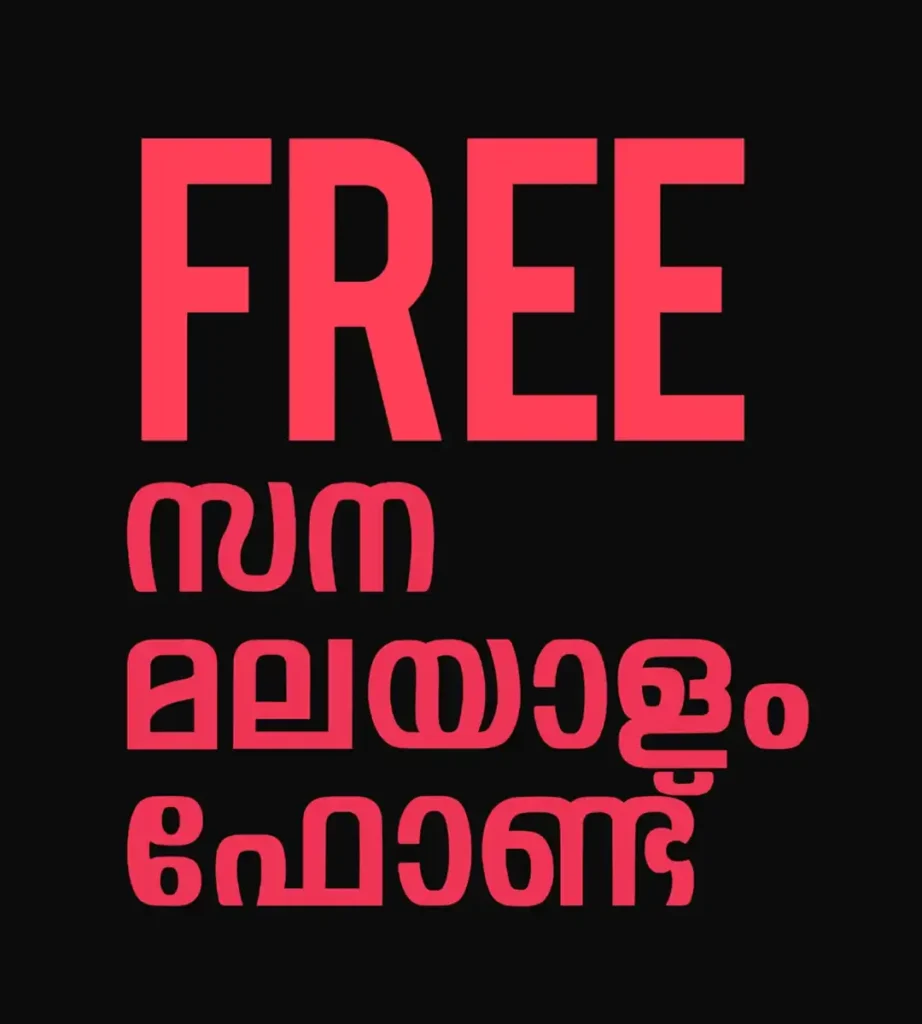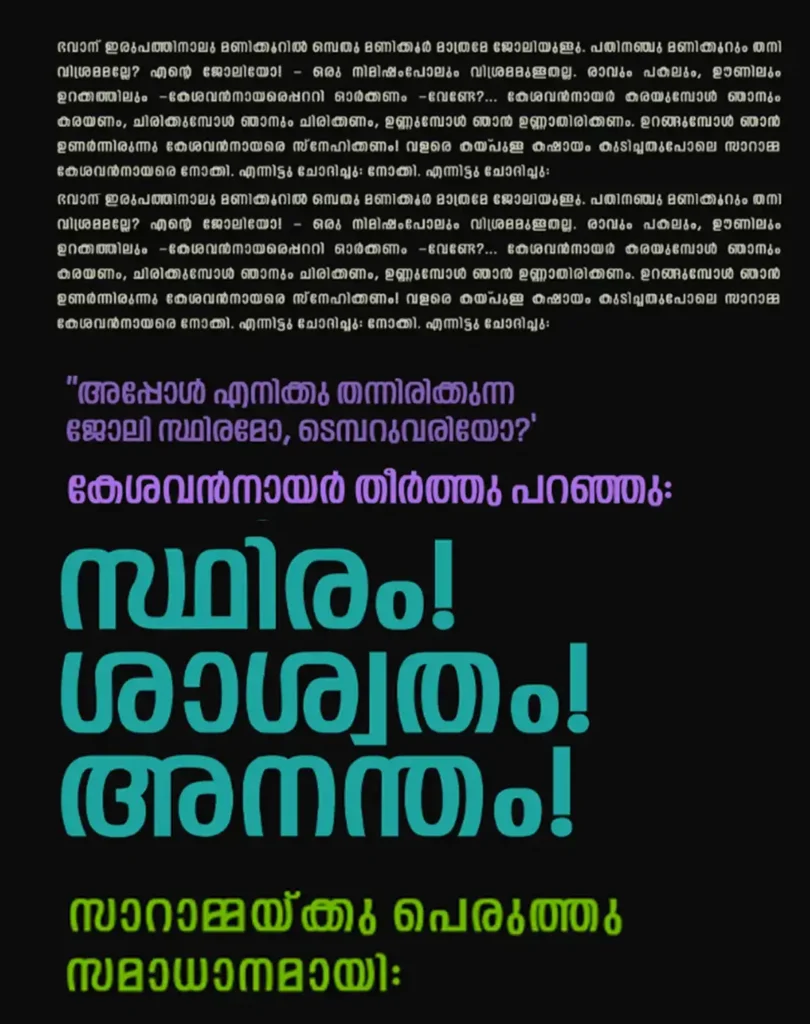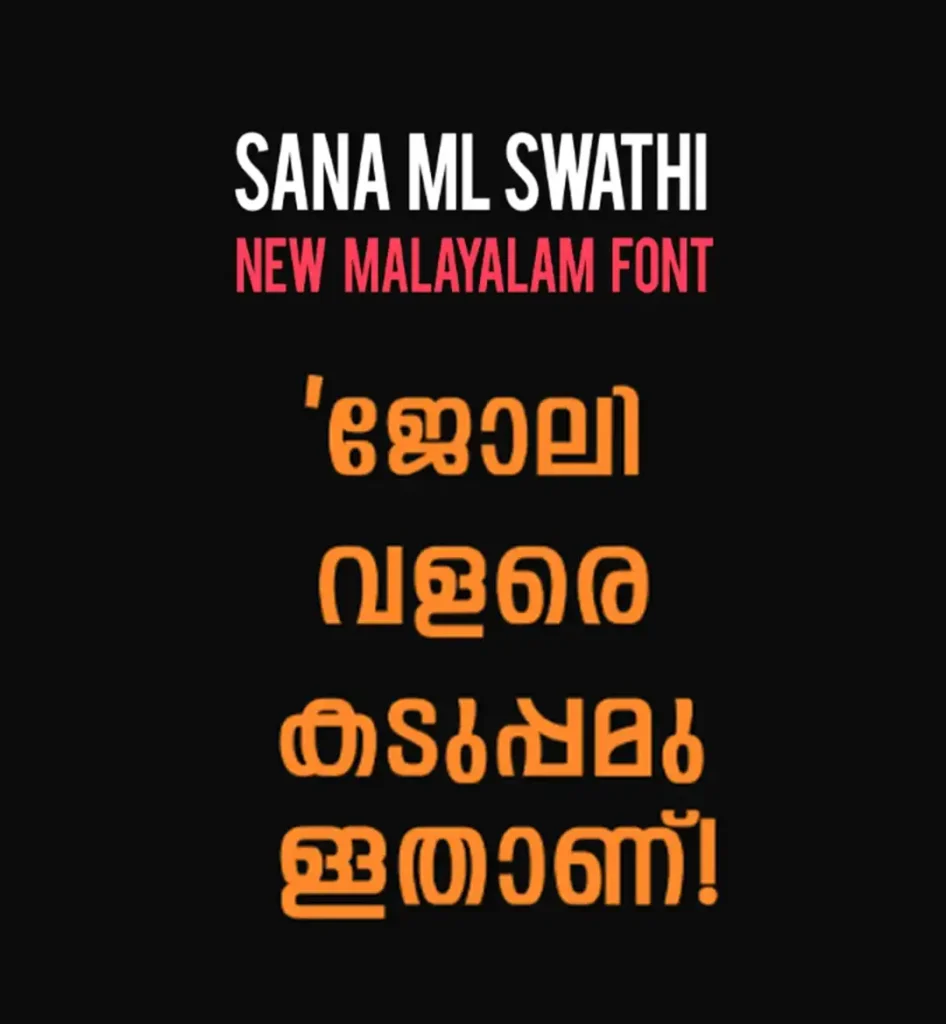
പുതിയ മലയാളം ഫോണ്ട്: Sana ML Swathi FREE Download!
ഡിസൈനിംഗ് ലോകത്ത് ഒരു പുതുമയോടെ എത്തിയിരിക്കുകയാണ് Sana ML Swathi എന്ന പുതിയ മലയാളം ഫോണ്ട്.
ഈ ഫോണ്ട് എളുപ്പത്തിൽ വായിക്കാവുന്നതും ഗ്രാഫിക് ഡിസൈൻ, പോസ്റ്റർ, സോഷ്യൽ മീഡിയ ക്രിയേറ്റീവുകൾ
തുടങ്ങിയവയ്ക്കായി ഉപയോഗിക്കാവുന്നതുമായ ആകർഷകമായ ലുക്കാണ് നൽകിയിരിക്കുന്നത്. ഭാവനാപരമായ
സ്രഷ്ടികൾക്ക് കൂടുതൽ ശൈലിയും സൗന്ദര്യവും നൽകാൻ ഈ ഫോണ്ട് സഹായിക്കും.